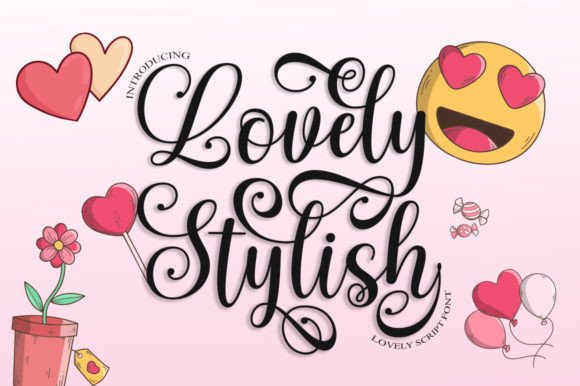
Lovely Stylish
Jika anda sedang mencari aset berkualiti tinggi seperti Lovely Stylish, pakej premium ini merupakan pilihan yang hebat untuk projek kreatif anda.
Sama ada anda mencipta produk POD (Print on Demand), jemputan perkahwinan atau grafik media sosial, Lovely Stylish amat bersesuaian.